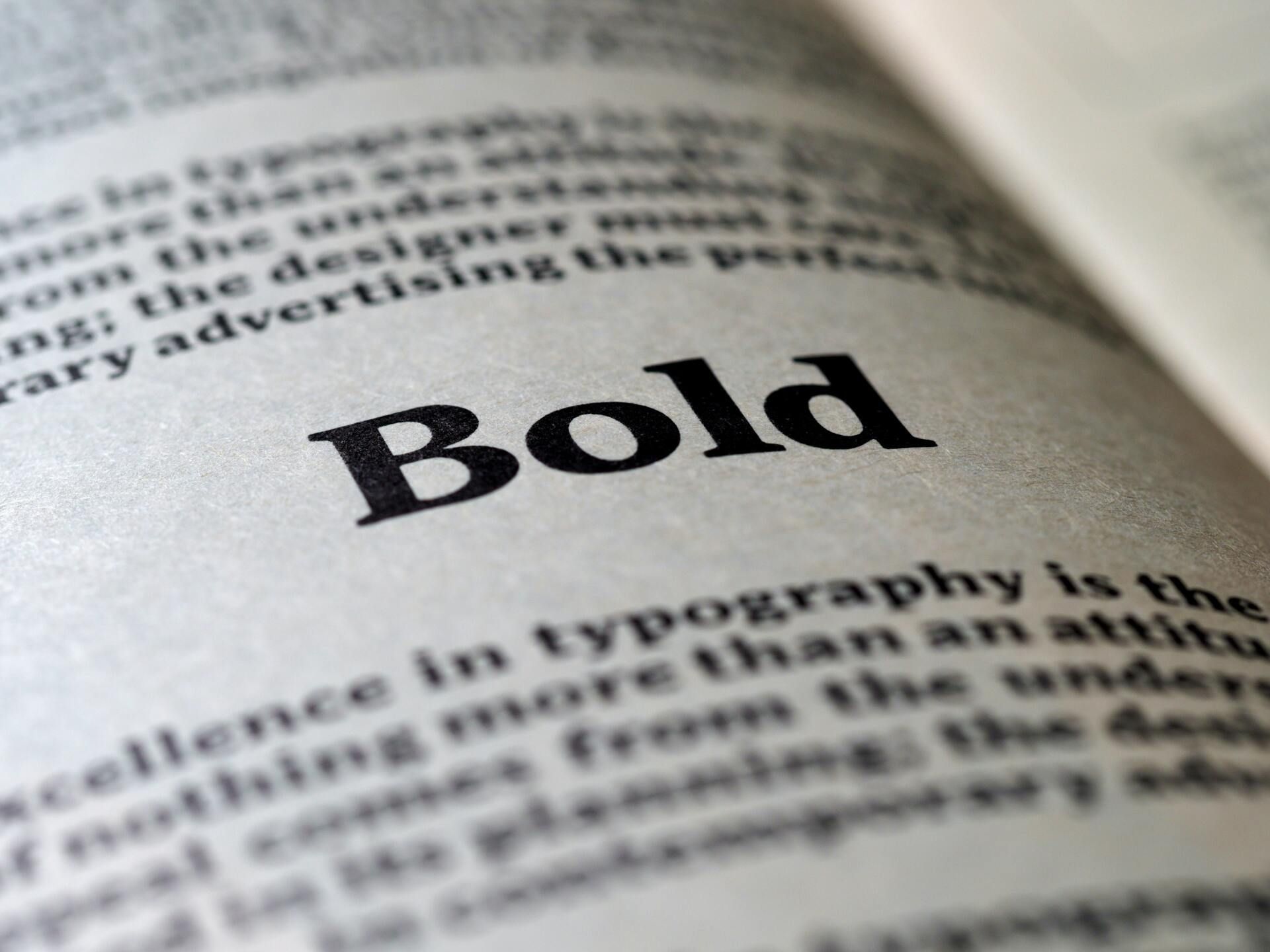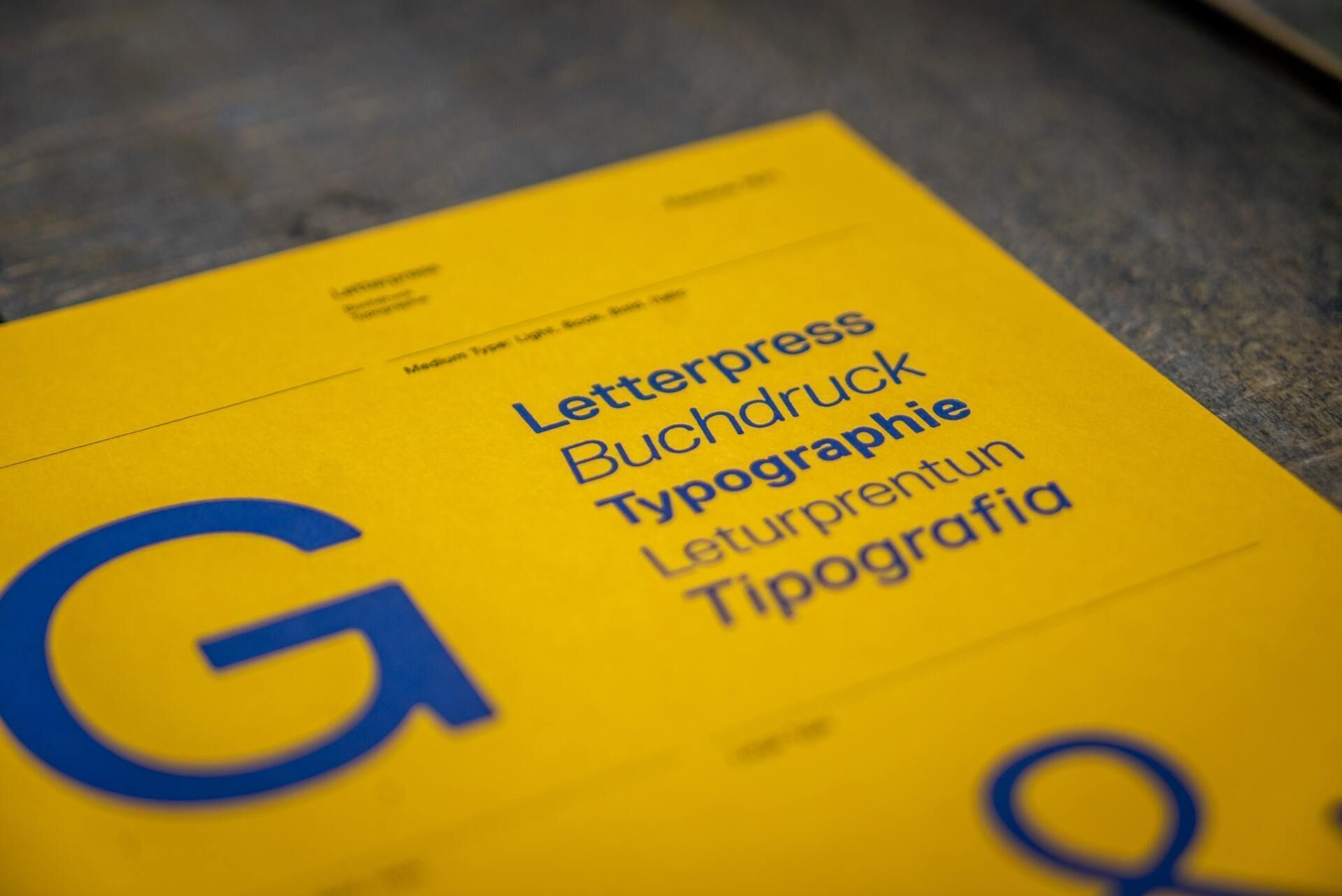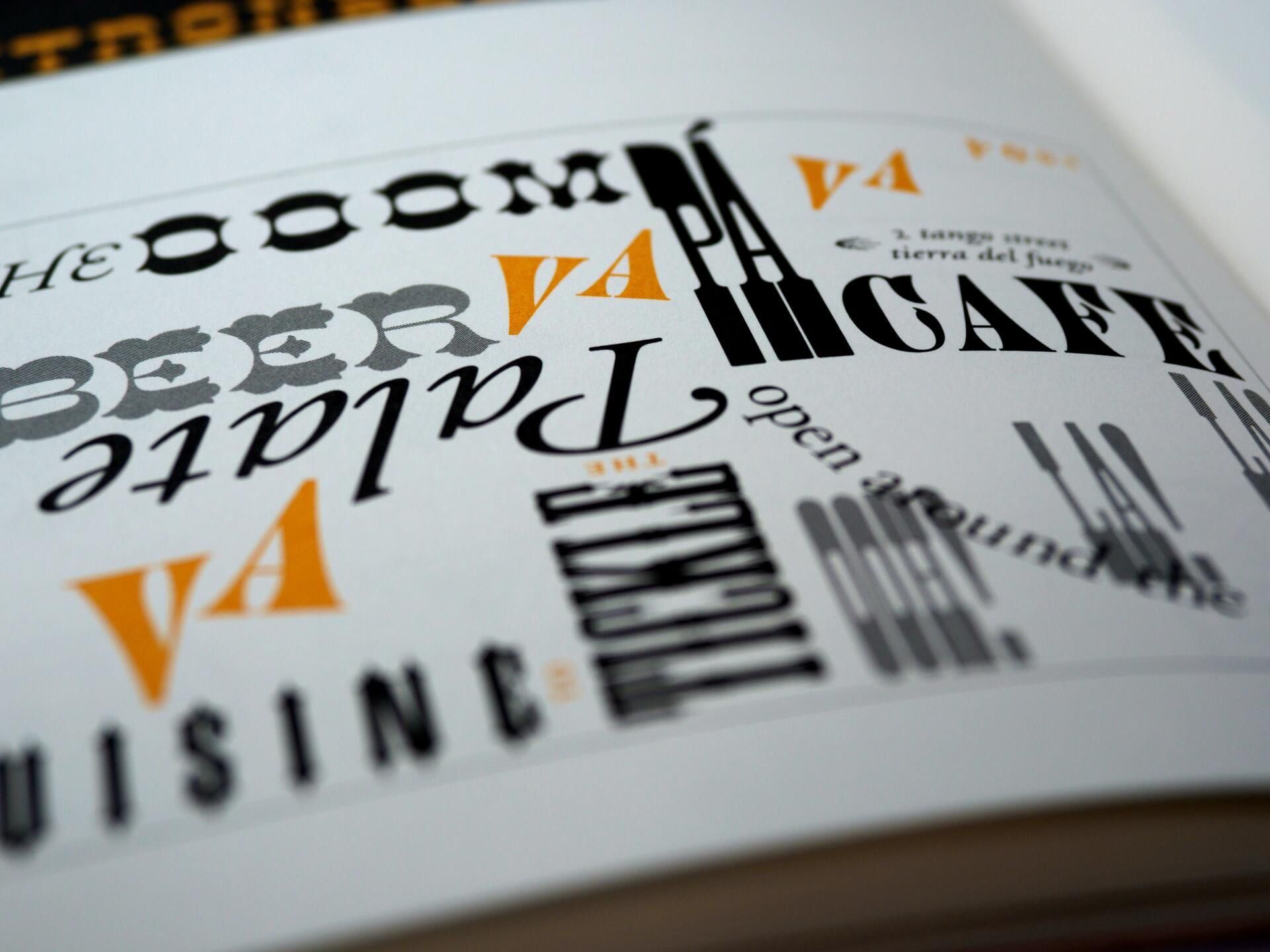
Cuál es la tipografía más adecuada para tu publicidad impresa
Las diferentes tipografías se utilizan para diversos fines, según el tono y la estética que intentes crear. Saber cuál es la idónea para tu marca es esencial para una estratégia exitosa de marketing impreso.
A veces, puede parecer que todas las marcas que conoces tienen una opinión sorprendentemente fuerte sobre las fuentes y tipografías, especialmente en lo que respecta a los anuncios impresos.
La discusión sobre las mejores tipografías para publicidad impresa continúa en todas las industrias y medios, y cada sector intenta descubrir las fuentes a las que su audiencia responderá mejor.
No se necesita un diseño gráfico para saber qué fuentes son más efectivas. Sin embargo, si gestionas el marketing desde una perspectiva que no es de diseño, elegir la fuente correcta puede ser complicado.
Después de todo, una fuente es mucho más que las letras que representa. Las fuentes son tan integrales para la marca y el éxito de su anuncio como los componentes más llamativos como las imágenes y el sonido .
Una “tipo de letra” o tipografía es un conjunto de letras, números y otros símbolos cuyas formas se relacionan mediante la repetición de ciertos elementos de diseño. Estas se aplican consistentemente para componer un texto o incluso se pueden hacer diferentes combinaciones de caracteres.
Aunque muchas personas llamarían a "Helvética" una fuente, es un tipo de letra. El software que le dice a tu pantalla o impresora que muestre una letra en "Helvética" es la fuente.
Los diseñadores conocen la diferencia entre una fuente y una tipografía, pero la mayoría de la gente no.
Entonces, en esta publicación, generalmente usaremos ambos términos, pero a nivel general, tipografía es el término común que la mayoría de la gente usa y entiende.
Una tipografía para cada proyecto
Elegir tipografías para proyectos de impresión es una tarea compleja.
También hay muchas otras cosas que debes tener en cuenta, y quizás la más importante es recordar que las fuentes a menudo se ven diferentes impresas en un sustrato que en la pantalla de tu computadora portátil o teléfono.
En este caso lo mejor es contar con la ayuda de un experto para no llevarte sorpresas desagradables, y analizar nuevamente las tipografías a utilizar para cada proyecto.
La discusión sobre las mejores tipografías para publicidad impresa continúa en todas las industrias y medios, y cada sector intenta descubrir las fuentes a las que su audiencia responderá mejor.
No se necesita un diseño gráfico para saber qué fuentes son más efectivas. Sin embargo, si gestionas el marketing desde una perspectiva que no es de diseño, elegir la fuente correcta puede ser complicado.
Después de todo, una fuente es mucho más que las letras que representa. Las fuentes son tan integrales para la marca y el éxito de su anuncio como los componentes más llamativos como las imágenes y el sonido .
Una “tipo de letra” o tipografía es un conjunto de letras, números y otros símbolos cuyas formas se relacionan mediante la repetición de ciertos elementos de diseño. Estas se aplican consistentemente para componer un texto o incluso se pueden hacer diferentes combinaciones de caracteres.
Aunque muchas personas llamarían a "Helvética" una fuente, es un tipo de letra. El software que le dice a tu pantalla o impresora que muestre una letra en "Helvética" es la fuente.
Los diseñadores conocen la diferencia entre una fuente y una tipografía, pero la mayoría de la gente no.
Entonces, en esta publicación, generalmente usaremos ambos términos, pero a nivel general, tipografía es el término común que la mayoría de la gente usa y entiende.
Una tipografía para cada proyecto
Elegir tipografías para proyectos de impresión es una tarea compleja.
También hay muchas otras cosas que debes tener en cuenta, y quizás la más importante es recordar que las fuentes a menudo se ven diferentes impresas en un sustrato que en la pantalla de tu computadora portátil o teléfono.
En este caso lo mejor es contar con la ayuda de un experto para no llevarte sorpresas desagradables, y analizar nuevamente las tipografías a utilizar para cada proyecto.
La tipografía más fácil de leer
Sentinel
Esta tipografía Slab Serif lo tiene todo. Si tu equipo de marketing está tratando de posicionarnos como líderes de la industria, Sentinel tiene las letras para hacer que tu marca parezca legítima.
Guión Hipster Pro
La cursiva no está muerta, todavía se usa ampliamente en la publicidad. Puedes optar por tipografías cursivas como Hipster Script Pro para contar una historia divertida y original.
Consejos para elegir la mejor tipografía
Com
binar adecuadamente el uso de tipografías con estas características hará que tus proyectos impresos destaquen, y en el buen sentido. Aquí hay algunas pautas rápidas destinadas a comenzar:
- Nunca uses tipografías de script para el contenido del cuerpo.
- Las fuentes Serif harán que el contenido del cuerpo sea más fácil de leer.
- Los tipos de letra Slab serif son perfectos para citas en bloque.
- Los tipos de letra sans serif deben reservarse para los encabezados.
- Los subtítulos deben ser script o serif para el mejor contraste.
- Comienza grande y ve progresivamente hacia lo más pequeño. Los bloques de contenido del cuerpo se pueden separar con un encabezado de tamaño mediano.
Las tipografías más utilizadas en publicidad impresa
Sonder Sans
Con versiones serif y sans serif, Sonder Sans es la fuente clásica, pero que ahora necesitas desesperadamente.
Si tus productos son antiguos o si planeas filmar un anuncio de video de estilo antiguo, el tipo de letra Sonder Sans puede completar el ambiente antiguo general que estás tratando de crear.
Cunia
Si quieres usar mayúsculas, no puedes equivocarte con Cunia. Las letras en negrita de este tipo de letra sans serif están ligeramente redondeadas para un efecto fuerte pero no abrumador.
Además, las letras gruesas y simples de la fuente se ven bien en diferentes fondos, incluido el fondo de movimiento rápido de un anuncio en video.
Dónde imprimir con la mejor tipografía
Parte de cualquier estrategia de diseño ganadora es elegir una fuente que cree una buena experiencia de usuario para tus clientes y resalte el sentimiento y el propósito de tu negocio.
En Geformas te ofrecemos una amplia gama de servicios de impresión, para llevar la publicidad de tu marca a un siguiente nivel.
La tipografía correcta realmente depende del mensaje que desees enviar a tus clientes y de las asociaciones que desee que tengan con tu marca.
Independientemente de la fuente que elijas, siempre debes pensar en cómo encaja con tu marca para crear una imagen más completa.
Un estudio reciente realizado por el psicólogo del MIT Kevin Larson mostró a los sujetos dos diseños de impresión diferentes: uno diseñado con mala tipografía y otro diseñado con buena tipografía.
Larson descubrió que el documento con una mejor elección de fuente tomó menos tiempo para leer y condujo a un mayor enfoque cognitivo y un "sentido de claridad más fuerte".